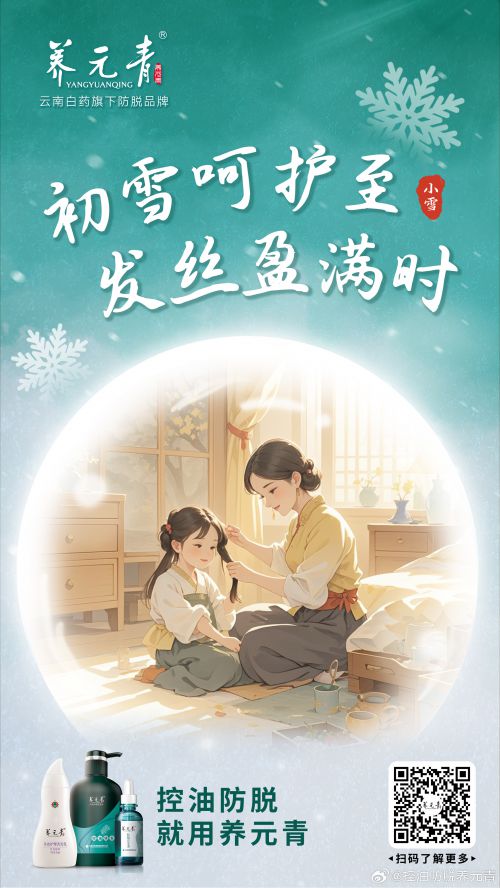
字家惜别行楷
字家惜别行楷是字家品牌旗下一款充满中国风韵味的手写行楷字体,支持会员商用授权。这款字体以“惜别”为名,将传统书法美学与现代设计需求巧妙融合,笔画细腻而不失力量,兼具手写的灵动与行楷的端庄。 字家惜别行楷字形修长,重心居中平稳,中宫宽博舒展,展现出优雅大气的视觉效果。其笔型灵动飘逸,点缀着精致的装饰元素,并通过圆头笔画与自然连笔的巧妙结合,形成了细腻的粗细对比,使每一个字符都富有节奏感和艺术张力。 作为一款手写体字体,字家惜别行楷不仅适用于艺术设计、广告宣传和产品包装,更能在文创作品、节日贺卡、邀请函等场景中增添独特的人文气息与艺术感染力。无论是追求古典雅致的氛围,还是打造温馨细腻的情感表达,字家惜别行楷都能以其独特的手写韵味,为设计作品注入灵魂。 字家惜别行楷以其独特的手写韵味和优雅的字形设计,成为中国风设计领域的理想选择。